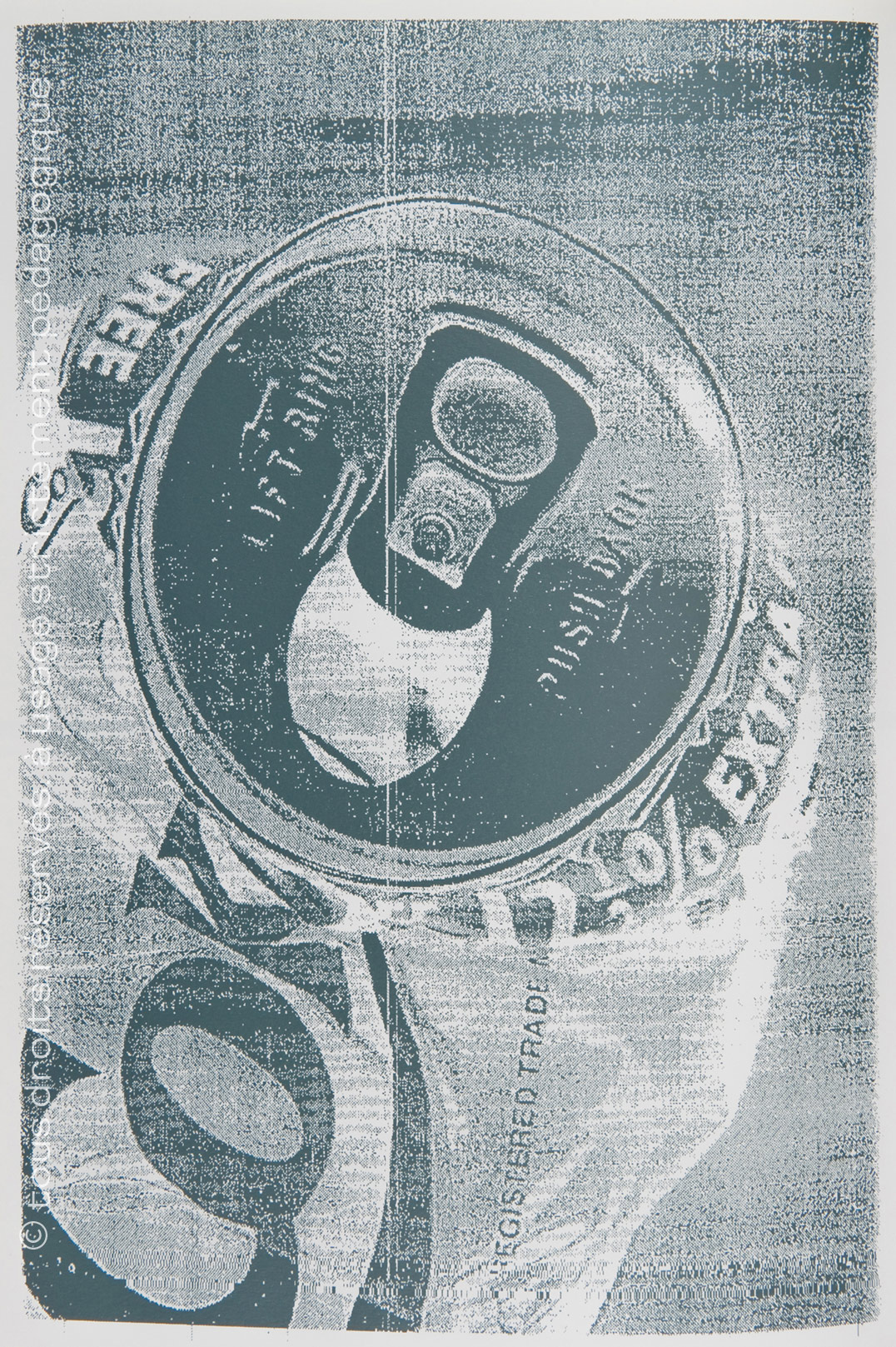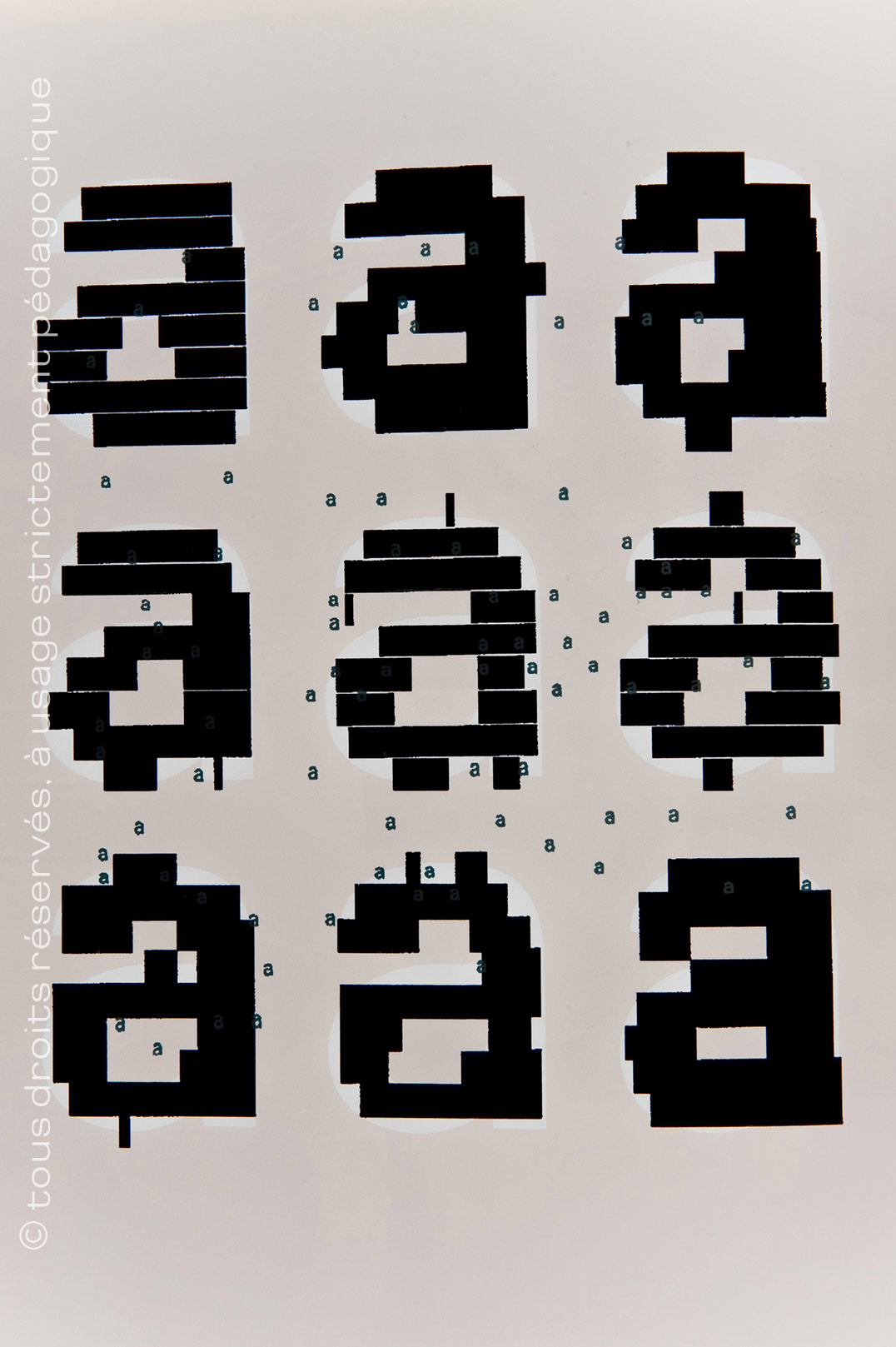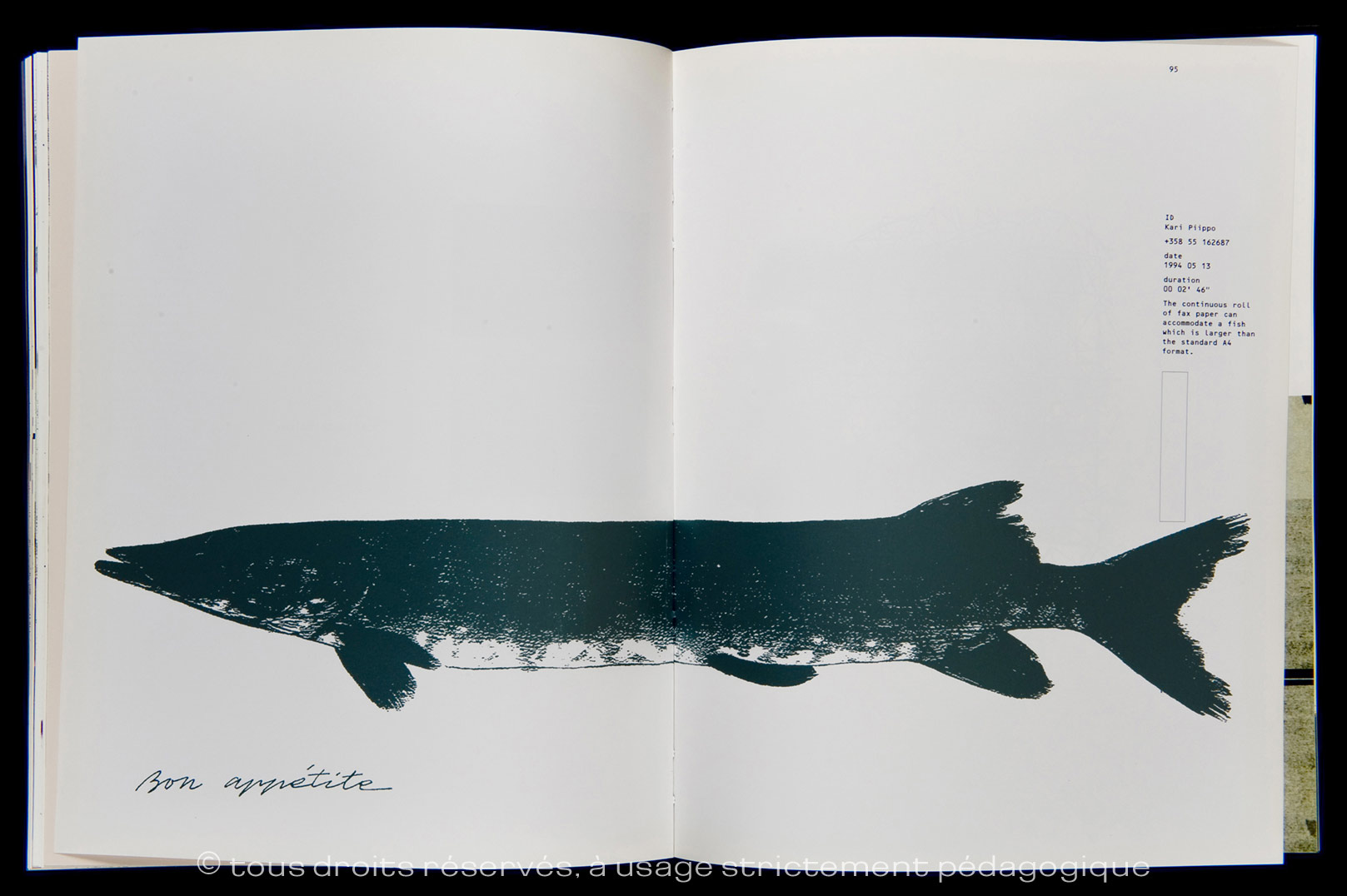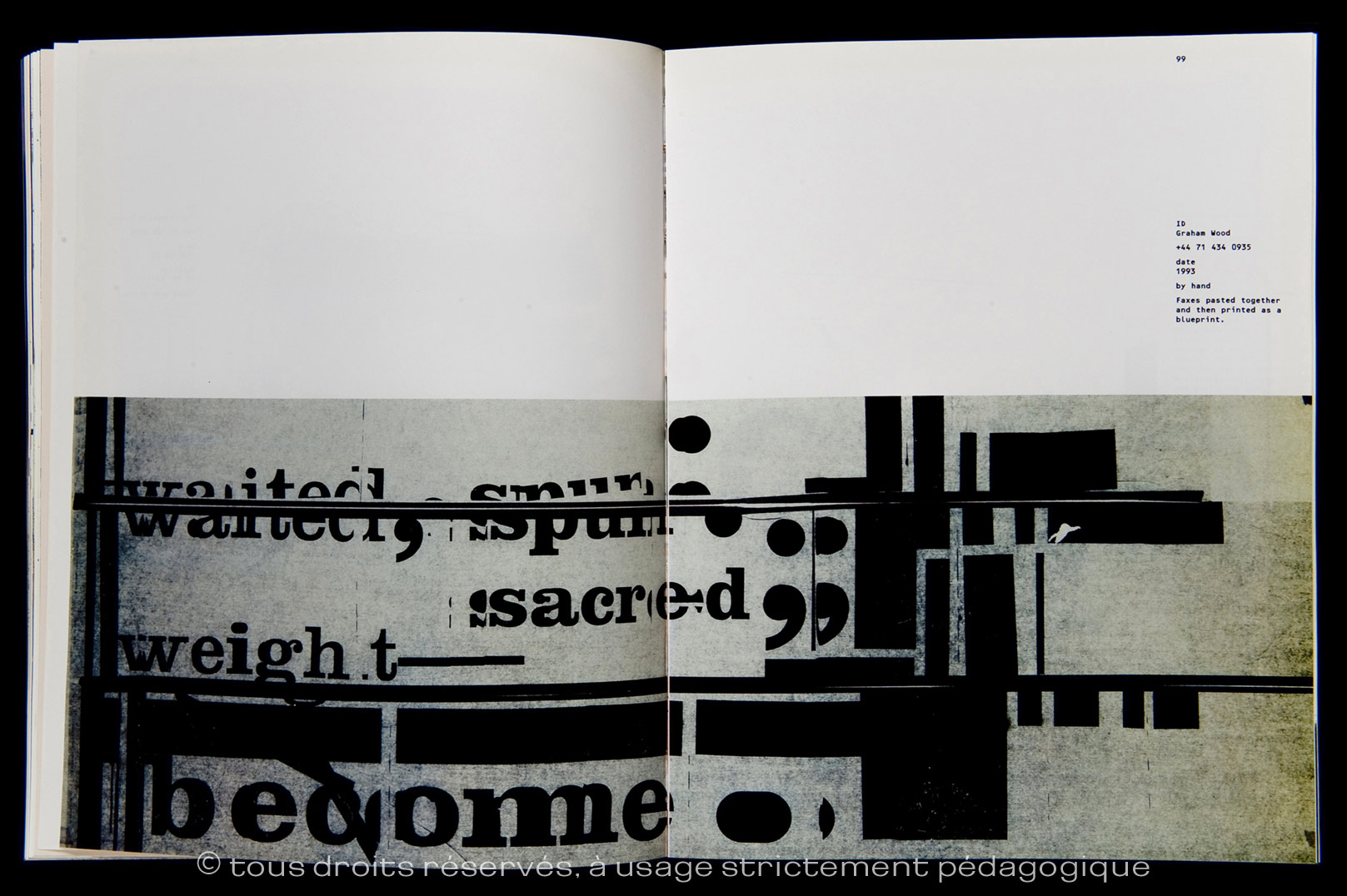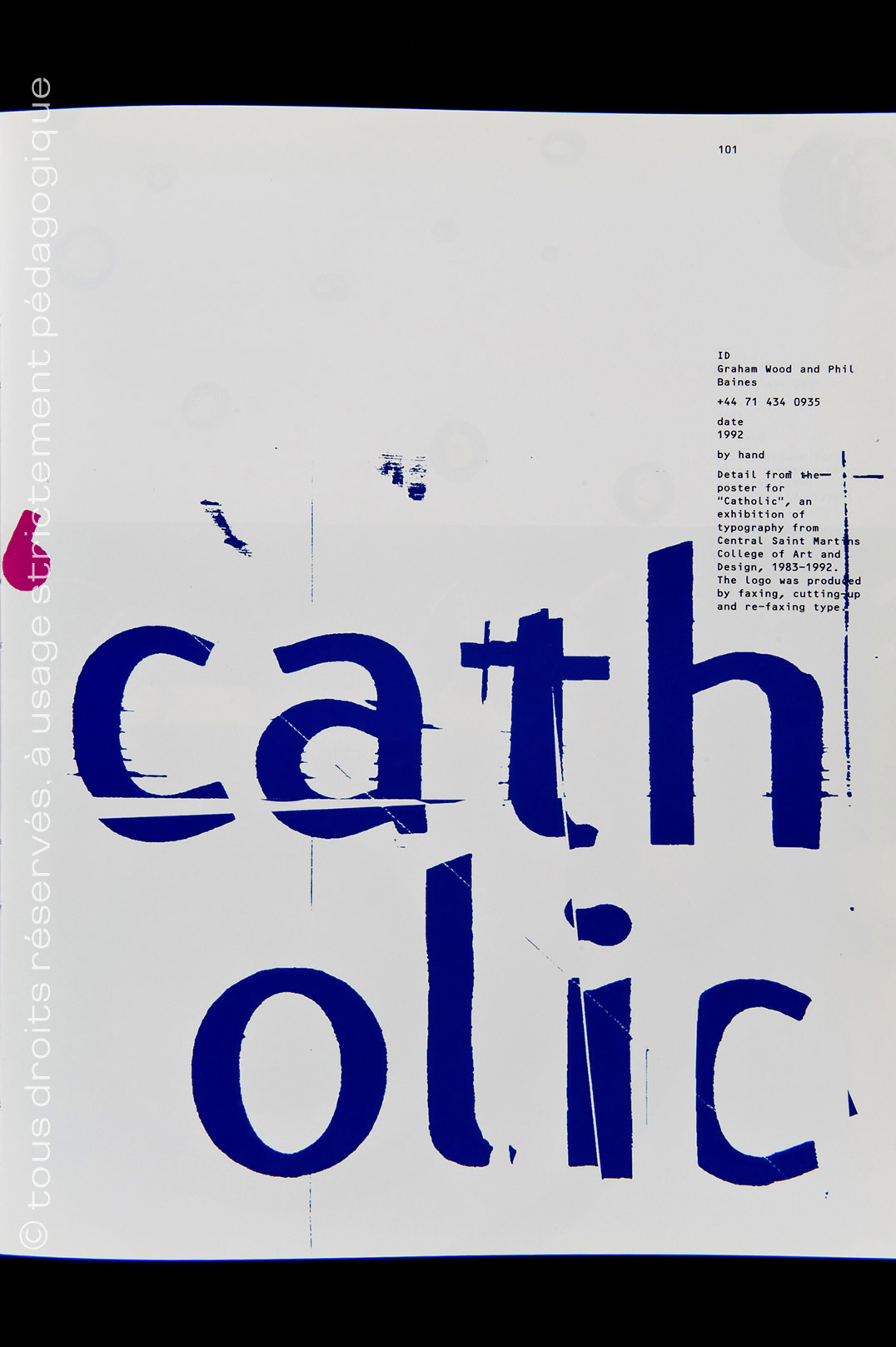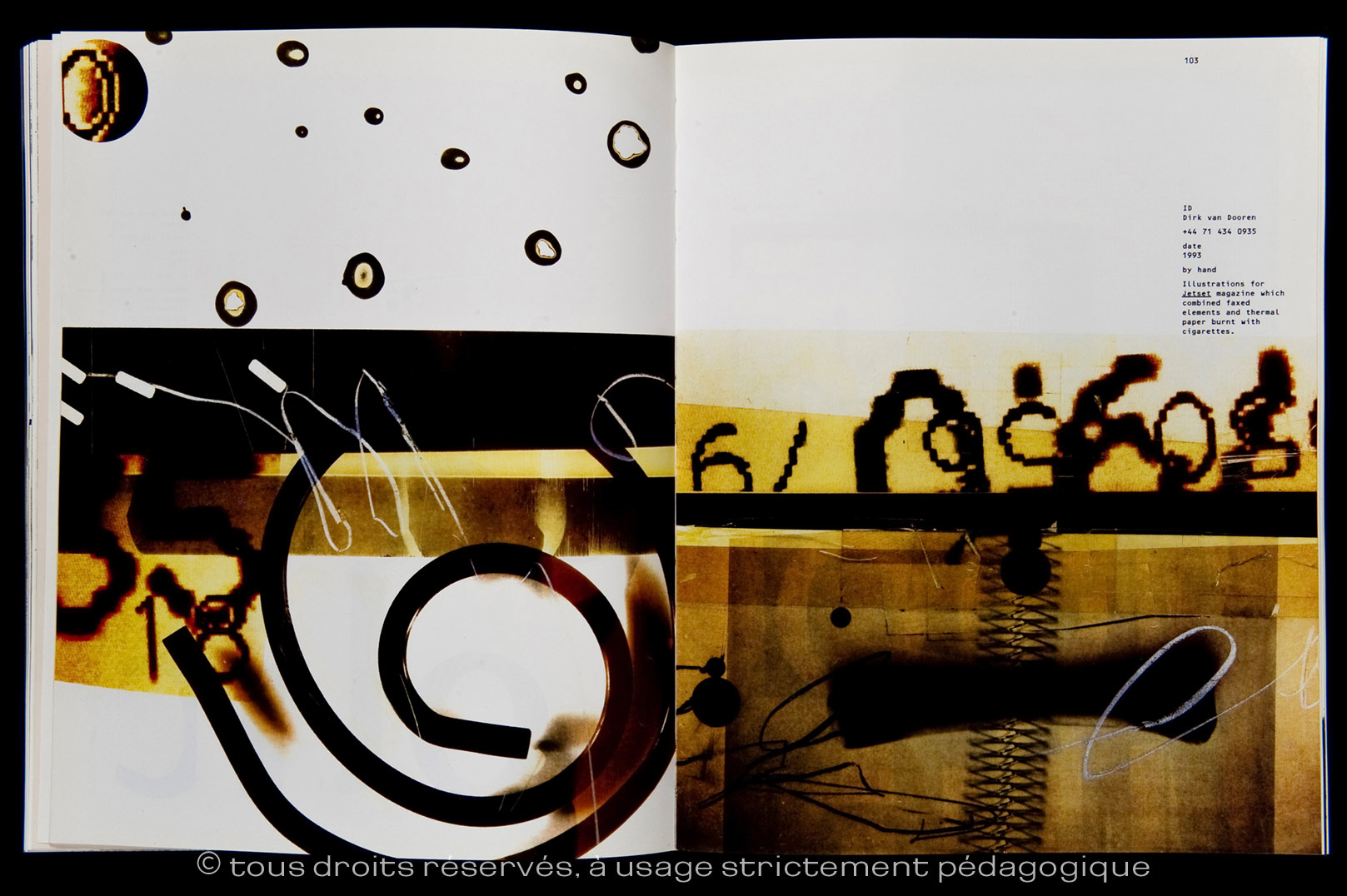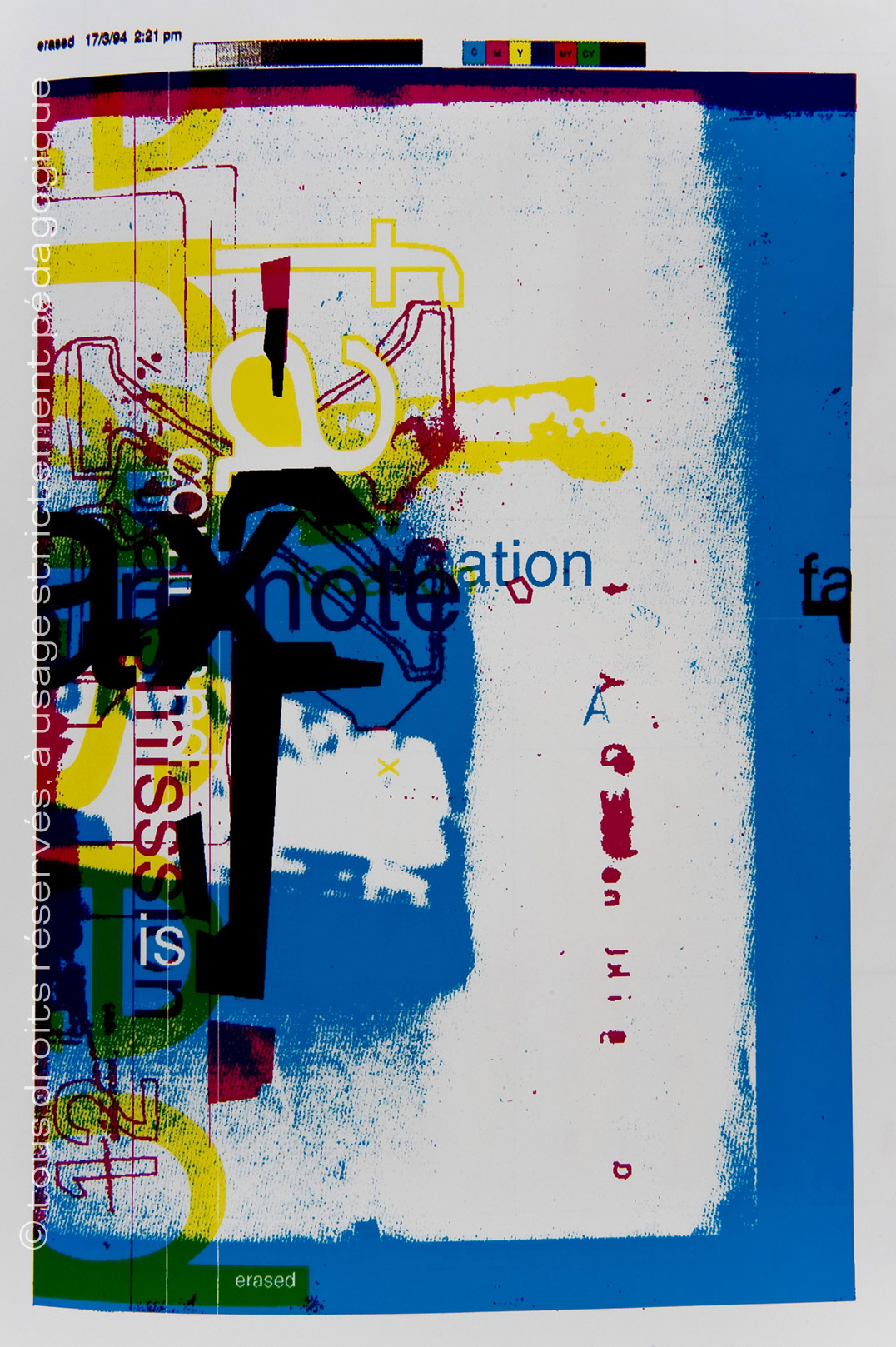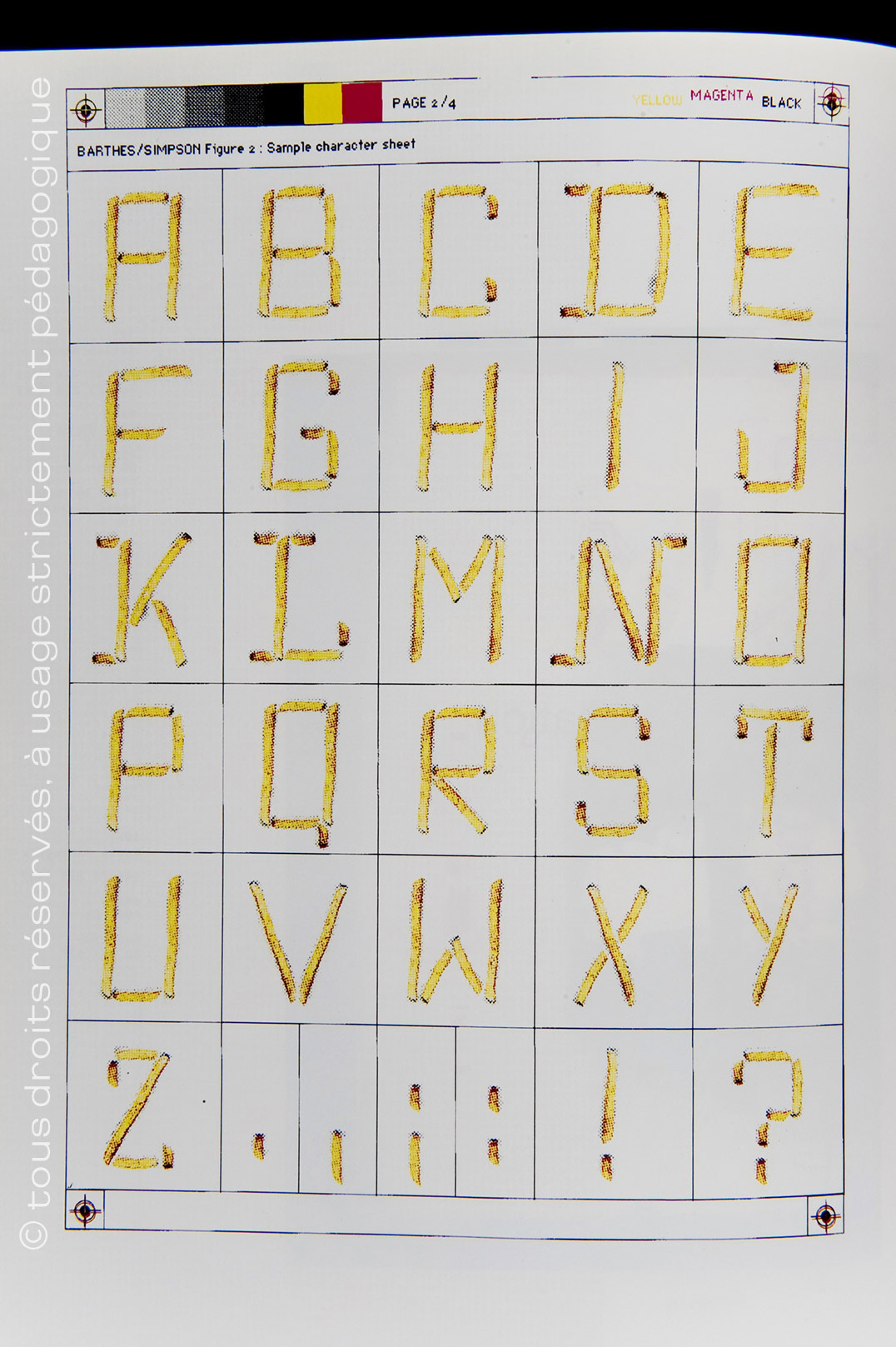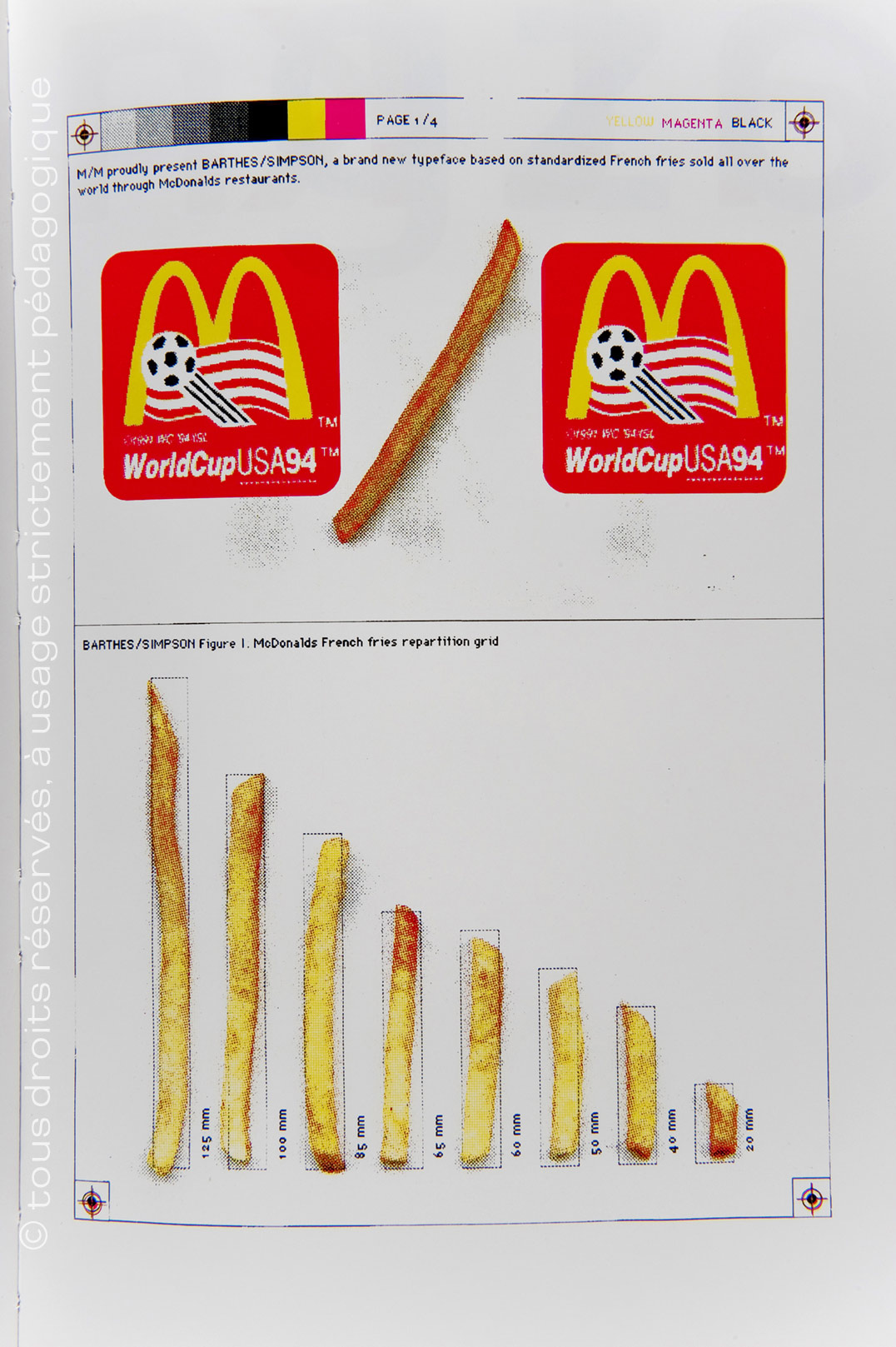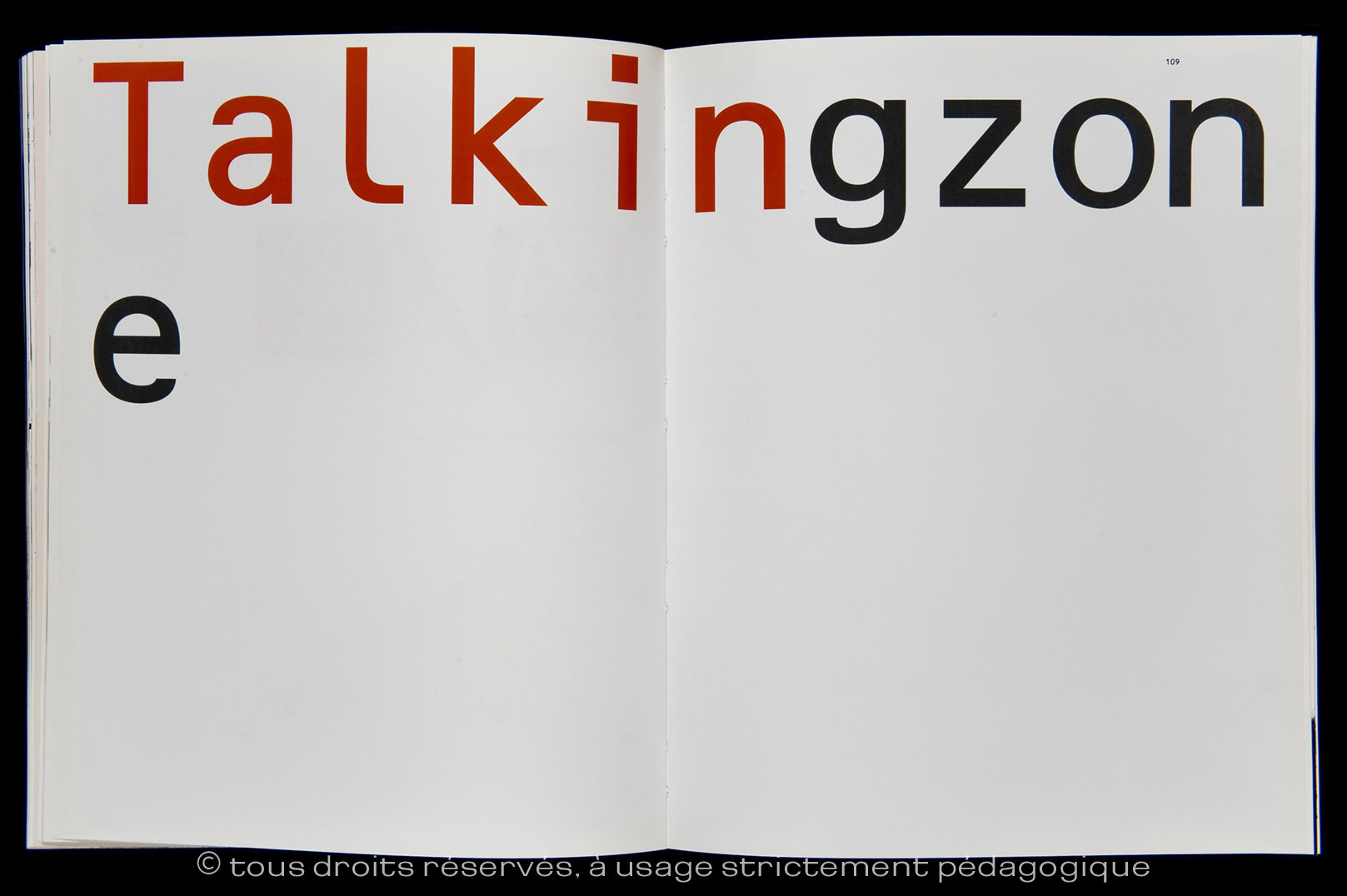
The Graphic Language of the Fax | de Edward Booth-Clibborn et Liz Farrelly (3/3)
Suite et fin de la publication de cet ouvrage emblématique des années précurseurs du monde numérique que nous connaissons désormais.
Les nombreux «Fax» que vous avez pu découvrir, sont l’œuvre d’artistes et designers qui comme je vous le disais précédemment ont récupéré, transgressé et détourné l’appareil Fax à des fins d’expressions graphiques et typographiques. L’outil, terriblement réducteur sur le résultat pixelisé n’est pas sans nous rappeler les aventures typographiques de Suzana Licko et de Rudy VanderLans, d’Emigre, qui ont dès 1984 créé un concept typographique basé sur le pixel. Si vous désirez de plus amples informations et notamment des indications sur les légendes et crédits, n’hésitez pas à m’écrire: peter (point) gabor (arobase) gmail (point) com.
Mais je vous laisse découvrir la suite et fin de cette publication :